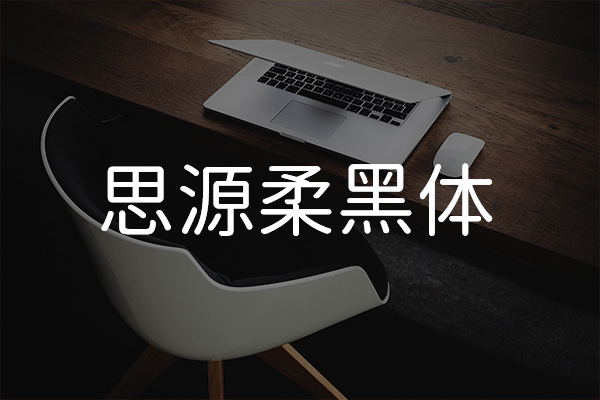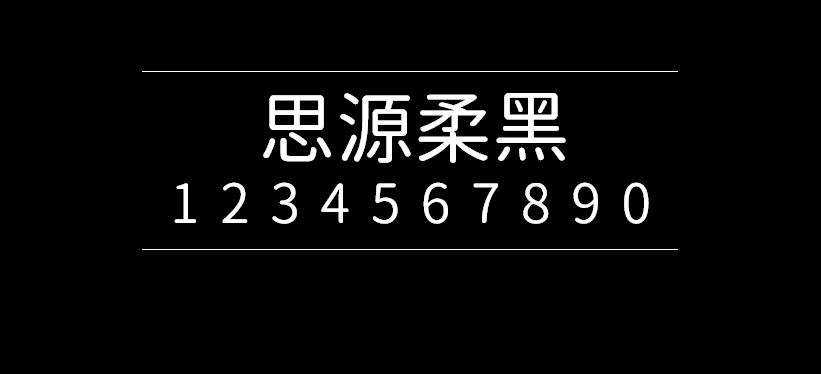
思源柔黑体
思源柔黑体(Gen Jyuu Gothic)是由日本自家製フォント工房 借由 Google 的开源字体「思源黑体」修改制作衍生而来,支持简体中文、繁体中文以及日文三种语言。字体开源并且无版权可免费用于商业用途,所以能应用的场景非常广泛。 「思源柔黑体」(源柔ゴシック) 与「圆体」比较相似,它继承了思源黑体的优雅设计以及可读性,并将文字的边角进行圆角化处理,使得整个字体看起来更加的可爱、年轻有活力,适用于很多设计、PPT制作、海报设计、Logo 设计等各类场景。 思源柔黑一共发布了 3 个版本,分辨是标准版、L、X。它们的区别在于圆角的圆润程度不同,L 圆角最小 (最尖),X 圆角最大 (最圆),而标准版则是介于两者之间。每个版本都有 7 种字重,3种字形样式 (包括等宽字体),大家可以根据喜好选择使用。 如果字体安装后在软件中找不到的话,请查找其日文名称「源柔ゴシック」一般就能找到了。字体在简体中文下有时候会遇到缺字现象,繁体字、日文则比较齐全。